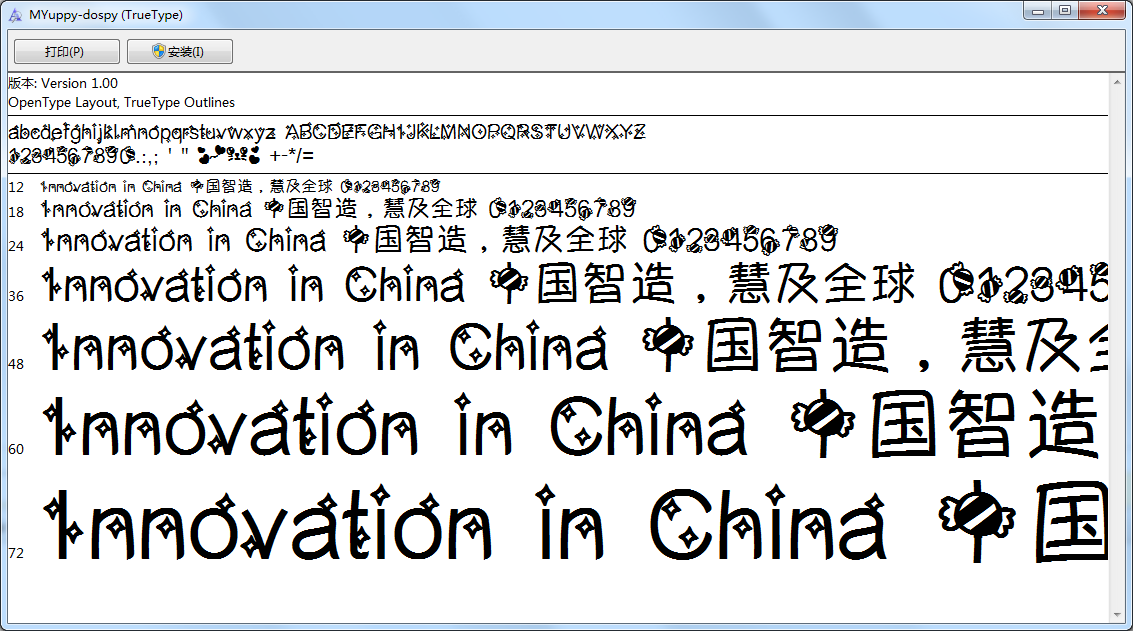
你像一顆糖字體是一款非常甜美可愛的字體,支持中文和英文字體,字體本身有點(diǎn)圓圓的,再加上中間的一些糖果點(diǎn)綴,非常的讓人感到甜蜜,喜愛的朋友趕快下載體驗(yàn)吧!
糖都是甜甜蜜蜜,現(xiàn)在字體也開始被設(shè)計(jì)的甜甜蜜蜜,當(dāng)然連名字都叫做你像一顆糖設(shè)計(jì)中文字體,糖果團(tuán)的搭配可以為素材增加一份魅力。